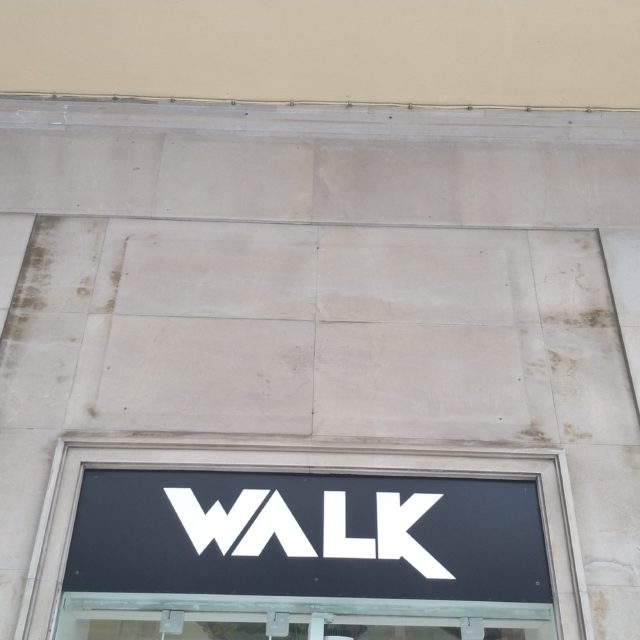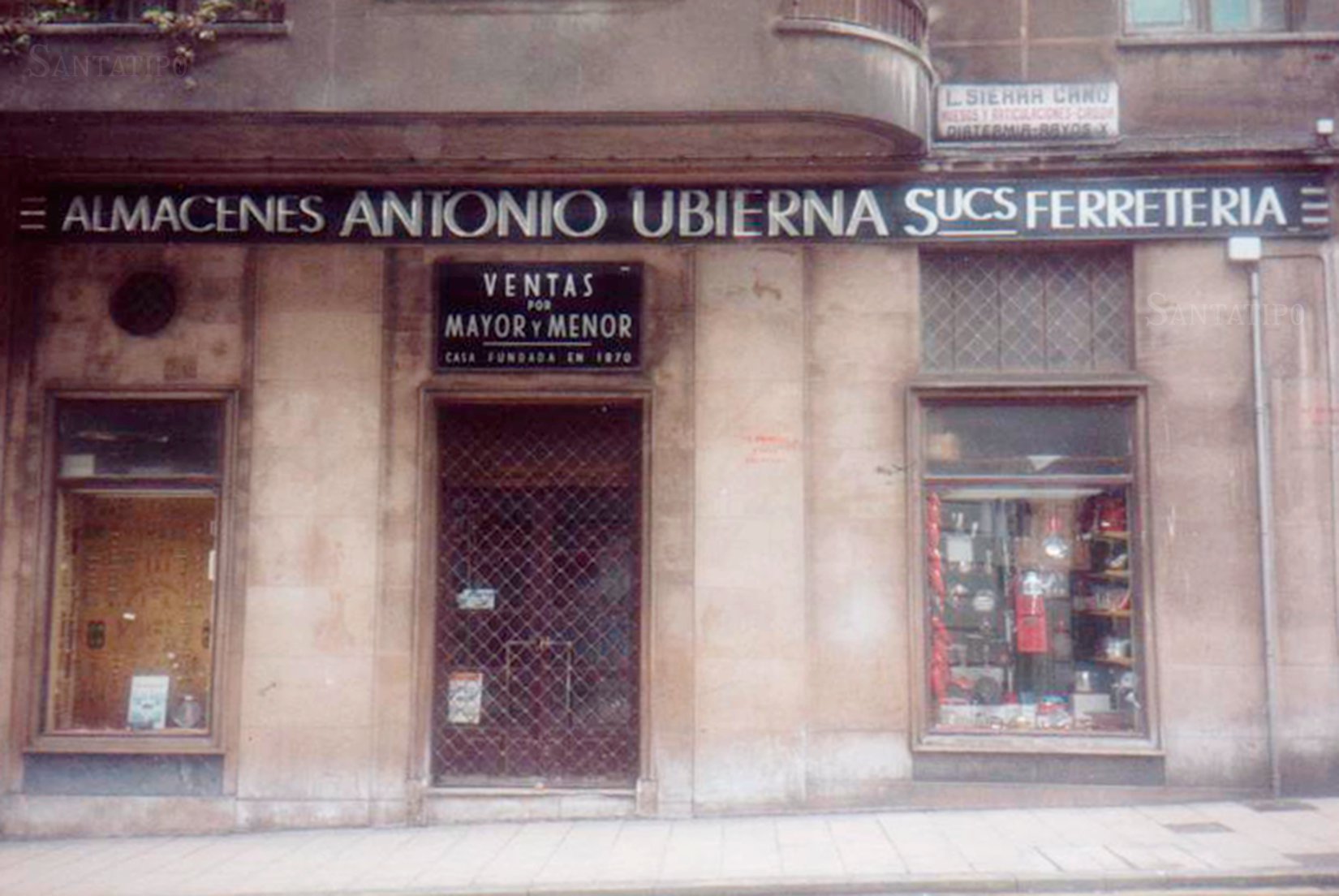
Ferreteria Ubierna
A finales del siglo XIX se abrió esta Ferreteria y Almacén de referencia de la ciudad. En esta imagen, se ve como se salvó del Incendio de 1941, junto a los Ultramarinos Oran. Y el despacho del Doctor Sierra Cano.
También vemos como en el edificio intervenido está el cartel de calzados Las Rojas «Antiguas de Las Rojas de Ramón Haya», uno de los comercios más antiguos y que no tuvieron tanta suerte. Fue uno de los muchos comercios que pasaron a los barracones y posteriormente se instalarían otra vez en Calvo Sotelo tras la reconstrucción.
Labores de los Bomberos en la calle Lealtad tras el incendio de 1941. Museo de los Bomberos de Santander / Colección del Campo Cruz. Centro de Documentación de Santander CDIS. Ayuntamiento de Santander
En los años 80 aún se podía ver este rótulo en vidrio, que posiblemente sea obra de NOVAL, y también una placa esmaltada anunciando al médico Sierra Cano, que como en la foto anterior tenía otro cartel.
Hoy no queda nada, excepto que si te fijas, se ven lo agujeros de la instalación del rótulo, tanto en la calle Lealtad como San Francisco.